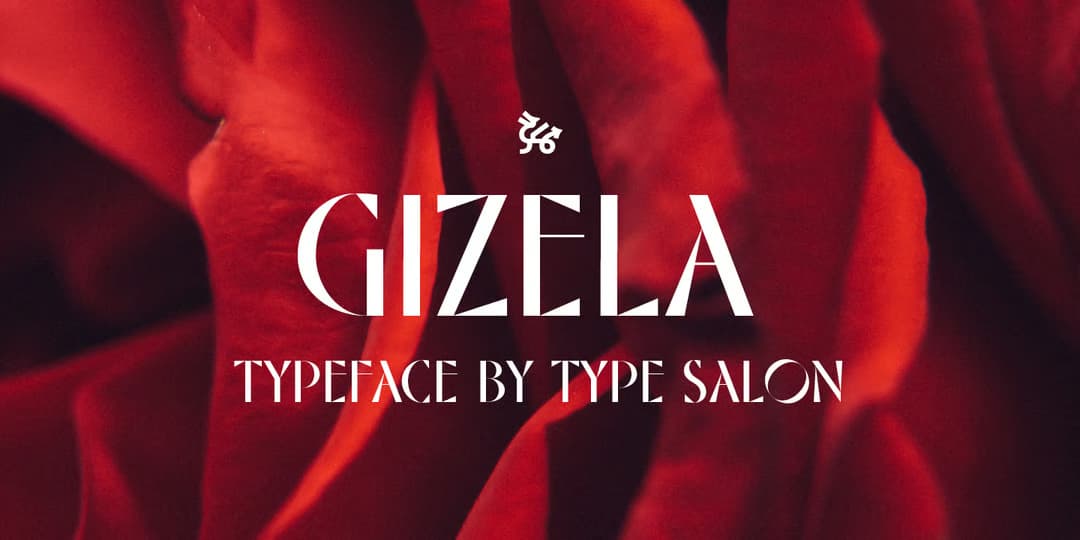
Gizela
レトロゴージャスなディスプレイ。アール・デコ風味のある豪華な雰囲気のディスプレイで、ジオメトリックで強コントラスト、コントラストが強すぎて一部ステンシルのようになっているおもしろい書体。大変シンプルながらすごく雰囲気があり、作者の腕のほどを伺わせる。ほんのちょっとだけリガチャーがあってバリエーションを出せるが、そのまま組んでも全然個性的。ハイブランドの香水などの広告によく似合いそう。大文字のみで1ウェイトのみ。